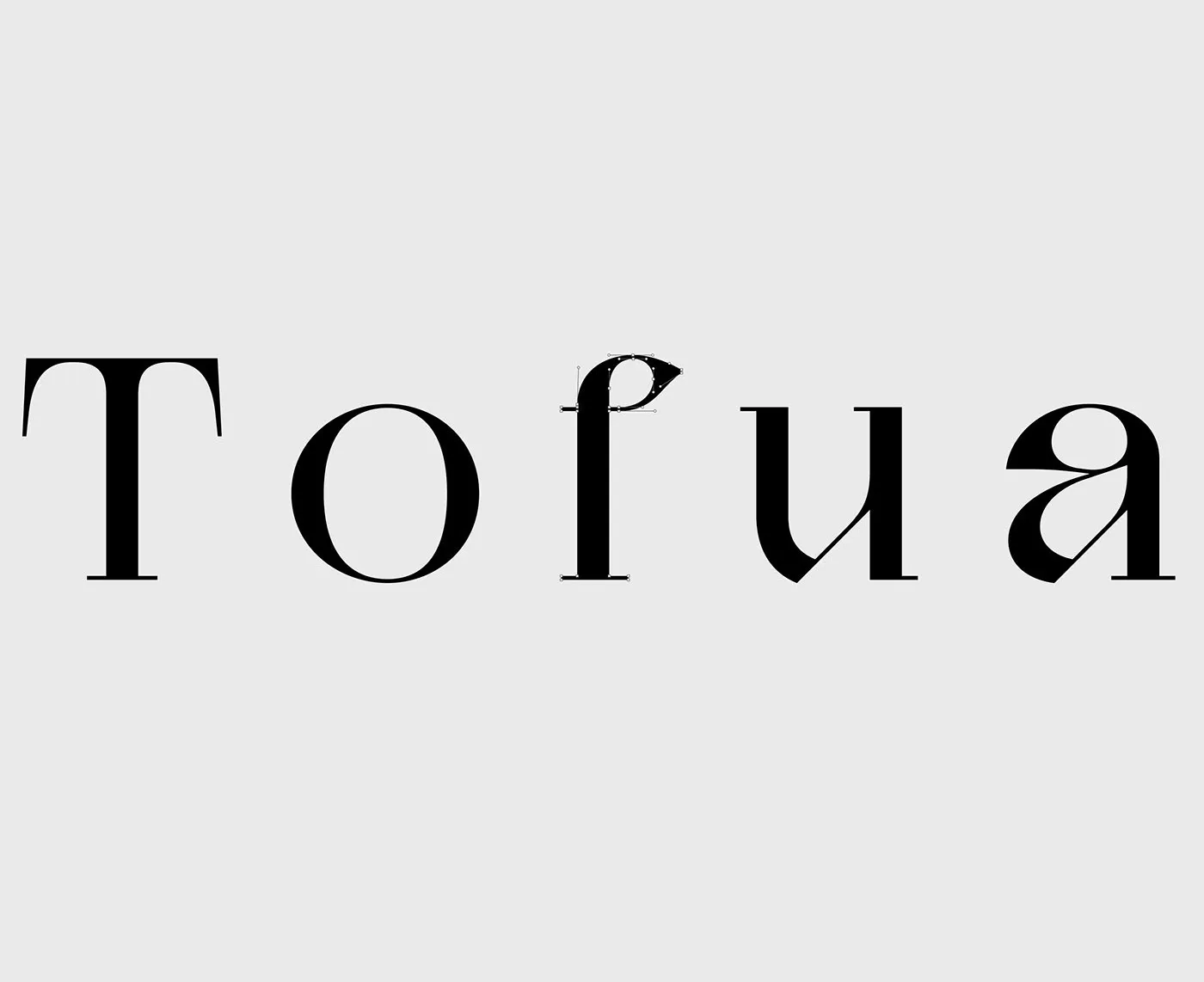
A Tofua Font é uma nova tipografia serif que surgiu com Muhittin Güneş em 2021. Esta elegante fonte proporciona suporte a várias línguas, números e marcadores de ponto e vírgula. A Tofua Typeface também oferece alternativas para caracteres normais e discretionary ligaturas, além de conjuntos alternativos com alfabetos gregos e romanos, garantindo uma experiência visual diversificada. Com um total de 505 glifos, a Tofua Font abrange desde a A até a Z em ambos os casos da escrita latina, assim como números e caracteres especiais. Seja você um designer ou editor de texto, a elegância e o cuidado na formatação que esta fonte oferece certamente o deixará impressionado.